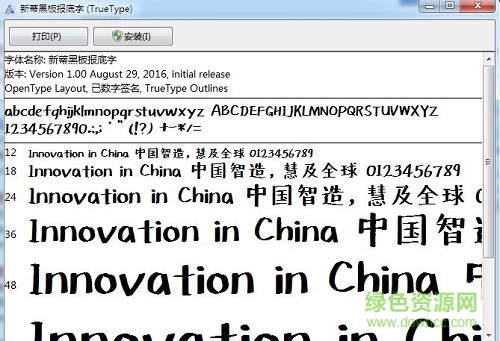
新蒂黑板報底字是一款漢儀打造的電腦字體,具有濃郁的手寫風(fēng)格,漢字看上去規(guī)整中帶點俏皮,英文字母閑的特別的有童趣,感興趣的朋友歡迎下載使用!
新蒂黑板報底字是一款根據(jù)黑板報常用字體打造的中文字體,字形微帶一點卡通風(fēng)格,效果非常不錯,還可以應(yīng)用于藝術(shù)設(shè)計、產(chǎn)品包裝、平面廣告、印刷等行業(yè)!